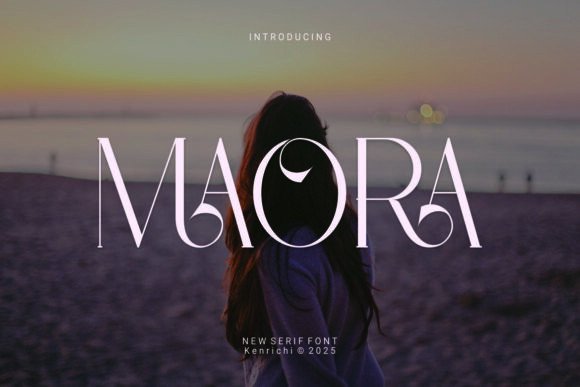
Maora Font
หากคุณกำลังมองหาเนื้อหาคุณภาพสูงเช่น Maora Font แพ็คเกจพรีเมียมนี้เป็นตัวเลือกที่ยอดเยี่ยมสำหรับโปรเจ็กต์สร้างสรรค์ของคุณ
ไม่ว่าคุณจะสร้างผลิตภัณฑ์ POD (Print on Demand) คำเชิญงานแต่งงาน หรือกราฟิกโซเชียลมีเดีย Maora Font ก็เหมาะสมอย่างยิ่ง